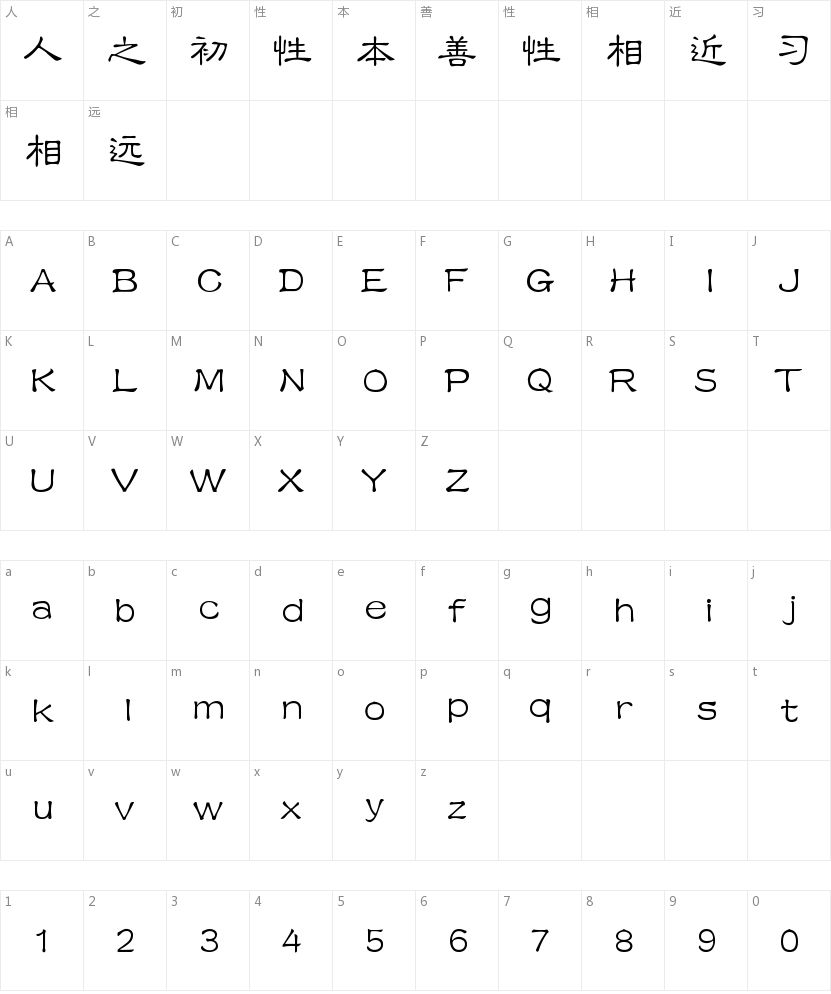
锐字云字库隶变体GBK
锐字云字库隶变体GBK字体是一款由锐字云字库推出的中文字体,它基于GBK编码标准,具有超过60000个中文字符,可以支持多种繁体字、简体字、符号、标点等,可以满足多种文字编辑需求。锐字云字库隶变体GBK字体拥有极具视觉冲击力的设计,具有非常强的美感,可以提升文字的表现力,使文字更加生动形象。此外,它还具有良好的识别率,可以提高文字的可读性,从而让文字更加清晰易读。
锐字云字库隶变体GBK是一款非常不错的手写艺术字体,具有很好的视觉感,适合于文化类的宣传设计、商业类品牌的广告和产品包装设计以及个性化文字排版等较多场景。